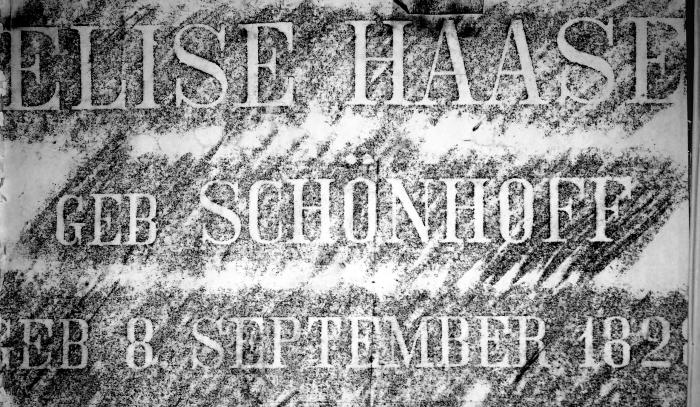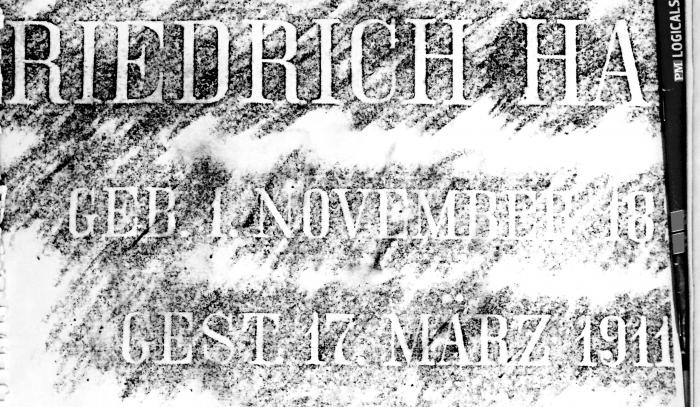
Grabinschrift, suche ähnlichen Font
Hi, ich bin neu und habe ganz sicher die einschlägigen Font-Webseites nach halbwegs passenden Schriften durchsucht ;-)
Die beiden Dateien sind kontrastverstärkte Fotos eines Abriebs von Grabsteinen, einzuordnen gegen Ende des 19.
Jahrhunderts. Es soll im Rahmen einer Restaurierung eine andere Grabinschrift ähnlichen Aussehens gemeißelt werden.
Auffällig ist der "aus dem Rechteck" konstruierte Charakter der Schrift und die gerade Linienführung. Und dann diese hübschen gerundeten Serifen... Auch brechen Zeichen und Zahlen (!) nicht aus dem Zeilenraster aus. Je länger ich darauf schaue, desto mehr verliebe ich mich in diese Schrift... Ich würde sie sofort kaufen, wenn ich sie fände!
Bei Bodoni oder Didot bin ich bereits gelandet. Aber so langsam kann ich keine kreisrunden C's und O's und D's mehr sehen. Davon ganz abgesehen passen die Serifen bei diesen Fonts auch nicht.
Hat irgendjemand einen Tipp für eine passenden Schrift? Ich wäre auch über geeignete Suchworte auf Englisch dankbar, welche die Schriftform beschreiben... vielleicht komme ich dann auf englischsprachigen Websites weiter.
Sieht mir aus wie eine preussische Schriftart mit Serifen. Normal ist sie sans serif. Fündig bin ich aber auch nicht geworden.
Das geometrische an der Schriftart wäre wohl als "square" zu bezeichnen, die runden Ecken als "rounded".
Die Serifen scheinen von der Times New Roman zu sein. Sie ähnelt der Times New Roman auch sehr, nur eben das sie nicht so rund ist.
Mit dem Suchbegriff "Berlin" bei Fonts findest du auch solche nicht runden Schriftarten, aber leider sans serif.
Ich wäre an dem Font auch interessiert.
Ich hab als "eckig" (geometric) jetzt mal diese Fonts gefunden, leider nicht mit so schönen Serifen:
Gerade bei Steinmetzarbeiten findet man oft Schriftarten, die nicht mit irgendeiner Satz-Schrift übereinstimmen. Die Schriftarten, die von Steinmetzen verwendet werden, wurden zumeist von einem ihrer Meister entworfen, und gehören so zu den größten Schätzen einer Steinmetzwerkstatt. Es ist zwar so, dass diese Schriftart sehr wohl von in dieser Zeit häufig verwendeten Druckschriften inspiriert wurden, aber auch von Schriften, die von Schildermalern gestaltet worden. Umgekehrt ist aber auch so manche der Werkssatz-Schriften von den handwerklichen Leistungen der Steinmetze inspiriert, so war beispielsweise Hermann Zapf von den Schriften, die er in Florenz in Stein gemeißelt vorfand so begeistert, dass er diese einfach skizzieren musste. Da er sein Notizbuch im Hotel vergessen hatte, benutzte er einen 1000 Lire Schein. Nach diesen Skizzen ist dann später die Schriftart Optima entstandenen.
Ich befürchte also, dass es zu den von dir gezeigten Schriftarten sehr wahrscheinlich noch keine digitale Schriftart gibt. Allerdings ist es durchaus möglich, nach deinen Skizzen eine anzufertigen. Wie schnell benötigst du diese Schrift?
Ich habe mir natürlich schon gedacht, dass hier keine 1:1 Umsetzung der Schrift zu finden ist. Das wäre ja einfach zu schön...
Ich bin mit dem Schriftbild der Ibis Display ziemlich zufrieden. In der Anmutung kommt die Schrift der Vorlage meines Erachtens am nächsten. Die runden Serifen kann man auch noch dranmalen, das ist wohl gängige Praxis. Ich hätte jetzt gerne 900,- Euro über, werde mich aber wohl mit einem Schnitt zufrieden geben müssen ^^
Das weiß ich nicht, ich habe nur die Vorlage gesetzt und mich ums Nachfragen hier gekümmert. Es klang eilig. Ich fürchte auch mal, das Budget lässt sowas nicht zu, sonst würde ich die benötigten Zeichen auch selbst vektorisieren (das wäre ja immerhin schon ein Schritt auf dem Weg zu einem benutzbaren Font ^^ - aber wirklich Erfahrung habe ich mit diesem Thema nicht)
Sodele. Bin gerade auf den Font der Ortstafeln gestoßen. Da gibt es eine Engschrift. Die ist zwar schön square, aber sans serif. Es ist eine Din 1451 Engschrift, oder auch Mittelschrift.
Die Grabsteinschrift ist eine Klassizistische Antiqua, die Serifen finden sich bei der Bodoni. Das ist aber nicht wirklich zielführend für "square". Der Fachbegriff für square nennt sich in englisch "condensed" und deutsch "Engschrift".
Mit dem allen zusammen führt das Ergebnis zur Abraham Lincoln:
Das kommt der Sache schon ziemlich nahe, wenn auch noch nicht absolut gleich.
… Die Bodini wiederum ist mit dem Antiqua-Fraktur-Streit(2) in Verbindung zu bringen, in dessen Zeit sie entstanden ist. …
Wieweit die Bodoni den Antiqua-Frakturstreit noch tangierte, kann ich nicht sagen.
Sicher ist, dass die Bodoni mehrere Jahrzehnte vorher entstanden ist, und nicht in dessen Zeit.